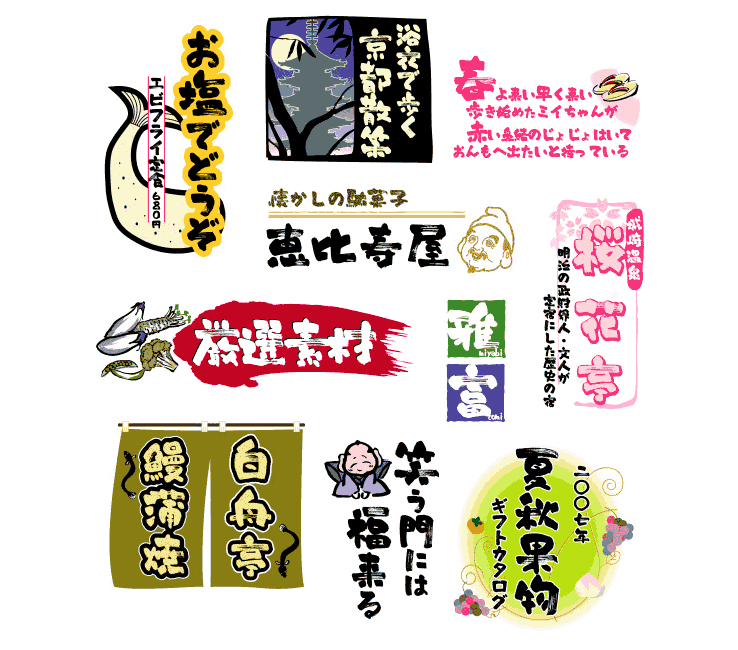
本製品の書体に含まれる漢字はJIS第1水準漢字全て2965字のみです。その他英数字・平仮名・片仮名・記号類・ギリシャ文字・ロシア文字・罫線が収録されています。機種依存文字は含まれていません。
【書体について】
花墨・花墨S(墨のかすれがシンプル)の2書体セット。プレビューフォントは「花墨」です。
本製品の書体に含まれる漢字はJIS第1水準漢字全て2965字のみです。その他英数字・平仮名・片仮名・記号類・ギリシャ文字・ロシア文字・罫線・機種依存文字が収録されています。
【書体について】
花墨・花墨S(墨のかすれがシンプル)の2書体セット。プレビューフォントは「花墨」です。
花墨